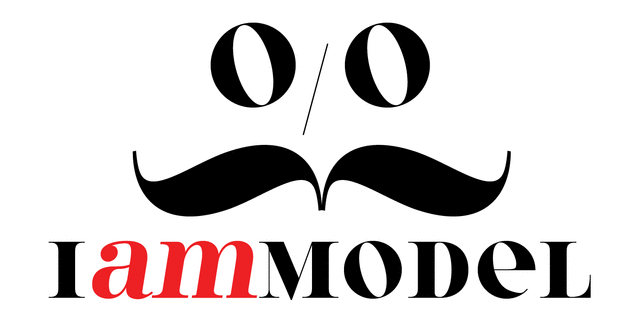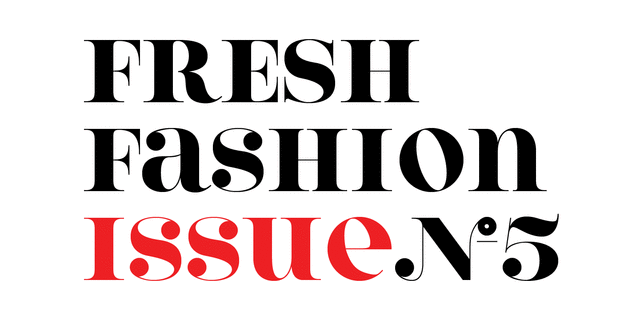
Шрифт для заголовков, плакатов и журналов. Разработан Сергеем Ткаченко в 2011 году.
эффектный, изысканный, оригинальный, модный, гламурный, праздничный, блестящий, роскошный, богатый, острый, глянцевый, характерный, манерный, претенциозный, пластичный, салонный, сексуальный, романтичный, мастерский, красивый, броский, привлекательный, экстравагантный, эстетский, нонконформистский, экспериментальный, гордый, театральный, драматичный, страстный, динамичный, прелестный, симпатичный